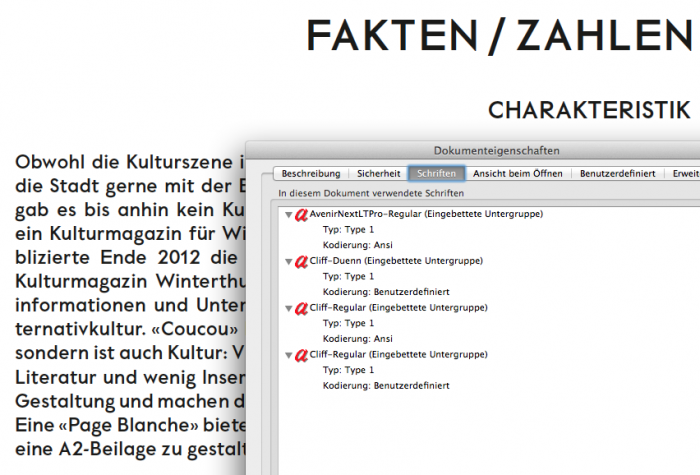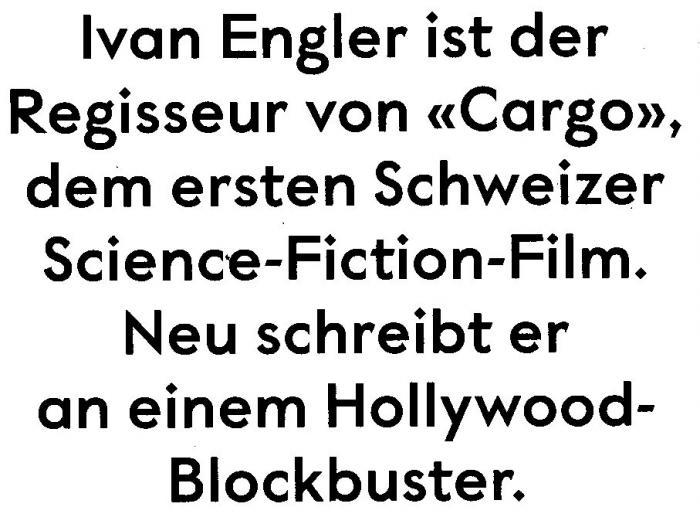
Titelschrift Coucou-Magazin
kennt jemand diesen font?
"Cliff" heißt die gute, finden kann ich sie allerdings nirgends.
Auf der Coucou-Website ist die Schrift als Coucou eingebettet. Bei der Namensvergabe war man sich anscheinend nicht ganz einig.
auf der büro-fax-website (http://www.buerofax.ch/?coucou) stehts: ...Die verwendete Schrift «Cliff Bold» wurde von Büro Fax entwickelt...danke euch, und ist tatsächlich eine mischung von aperçu, value und evtl auch noch der underground.